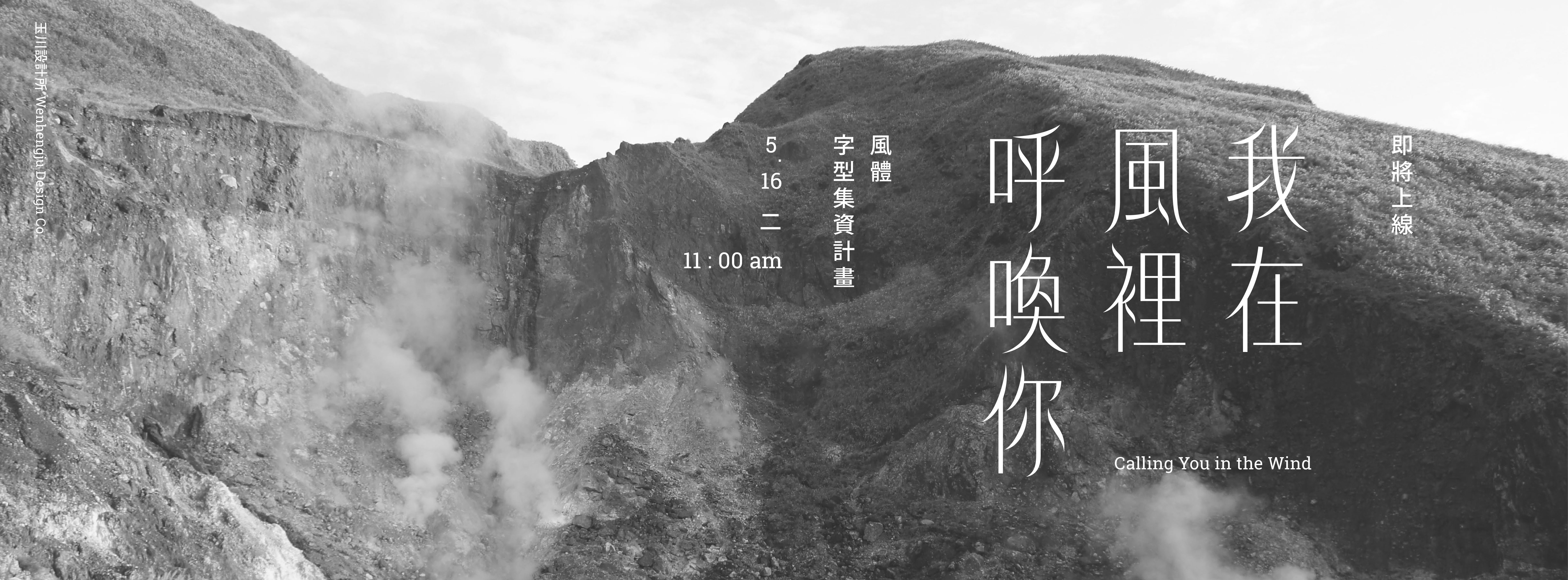
我在風裡呼喚你 — 風體 Wind Font 字型集資計畫
集氣再登場!
風體 Wind Font 字型集資計畫正式啟動
千呼萬喚終於來到這一刻
你好,我是風體設計者温珩如。從上次的風體初展到現在也有一年多的時間,感謝有你們的熱情支持,風體終於要在嘖嘖集資平台上與大家見面,
也終於有機會讓這套繁體中文創意字型能夠問世。
風體:悄悄地乘著風,為字型拂來新的氣象
想讓字型不只是字型而已,這是風體想要傳達的最重要的一件事。字型是一件設計作品,但字型不只是具有實用性,它也可以有美的收藏價值。當你看著風體,可以感受到它的溫柔、它的溫度、它的生命力;透過各種材質和形式,表現和襯托出字體的靈魂,字型也就被賦予了嶄新的面貌。
排除萬難,風體要和你們一起完成挑戰
風體字體設計是一項獨立開發的計畫,雖然僅僅是 7,000 字的常用繁體中文字符與英數符號,對於沒有資金與資源的獨立字體設計來說,都是一項艱鉅的任務和挑戰。儘管如此,風體仍要和你們一起跨出這一步:每一個你所支持的一小步,都是風體前進的最大動力。有你的一同參與,能讓臺灣字型市場越來越豐富多元,也讓越來越多人了解字型產業的專業性與重要性。
超級方案,獻給每個對風體有愛的你